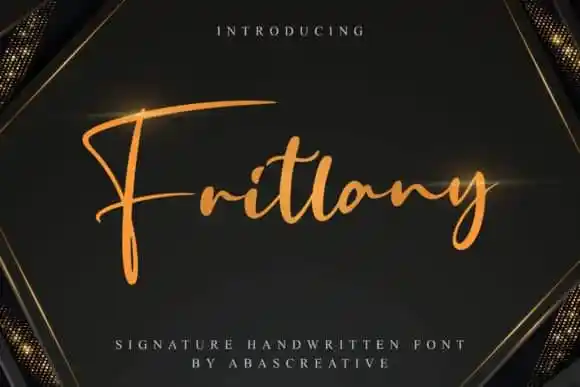
A fonte Fritlany Script é uma escolha perfeita para quem busca a essência do design elegante e minimalista. Com sua tipografia script minimalística, este fonte inclui ligaturas e estilos alternativos, tornando-o um ótimo complemento para os projetos que exigem um toque delicado de escrita manual. Este é um estilo de tipo contemporâneo inspirado no formato da mão escrevendo, ideal para criar designs únicos e distintivos. Com sua elegância sob medida, a Fritlany Script está perfeitamente adaptada para aplicação em cartões de convite para casamento, cartas de agradecimento, cartazes de citações, cards de lembrança, logotipos, cartões de negócios e muito mais. Suas linhas suaves e sutis dão um toque único à sua próxima criação visual. A fonte Fritlany Script é o resultado do trabalho artesanal de um designer talentoso da 99designs chamado AbasCreative, que criou um design singular, delicado e eterno. Com uma aparência avassaladora em qualquer projeto, a Fritlany Script torna-se um recurso indispensável para quem busca adicionar nuances de escrita manual ao seu design.